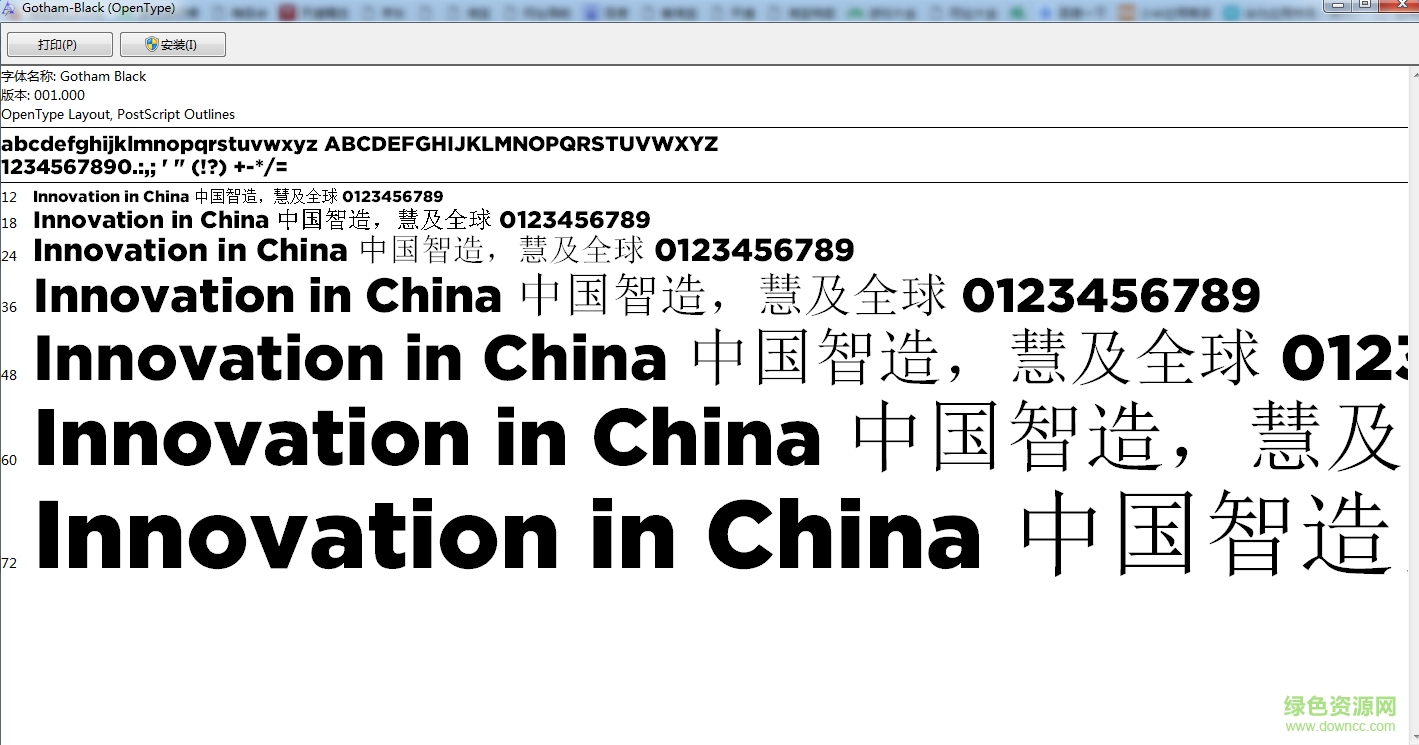
gotham black字體是一款具有黑體字特點(diǎn)的英文非飾線體,該字體點(diǎn)畫線條結(jié)構(gòu)都非常精細(xì),具有一種現(xiàn)代機(jī)械感,本站為大家免費(fèi)提供這款字體,歡迎下載!
大寫的非飾線體最早出現(xiàn)于公元前460至前430年的古希臘伯里克利時(shí)代的雕塑和碑刻中,在埃及的希臘風(fēng)格時(shí)期,也常常出現(xiàn)在寺院的頒令、墓碑石和出土的陶罐繪紋上,最著名體現(xiàn)這一風(fēng)格的,是刻有五十四行古希臘大寫字母的羅塞塔銘文(Rosetta Stone)。公元前三世紀(jì)的古羅馬書寫體系中也包含非飾線體風(fēng)格。從東西羅馬帝國時(shí)期,到公元后十五世紀(jì),大寫的非飾線字樣一直被應(yīng)用于許愿、圣餐和祈禱等宗教活動(dòng)中。他們也出現(xiàn)在硬幣圖案、蠟封圖章、大獎(jiǎng)?wù)?、墓碑石和建筑立面的雕刻上?/p>